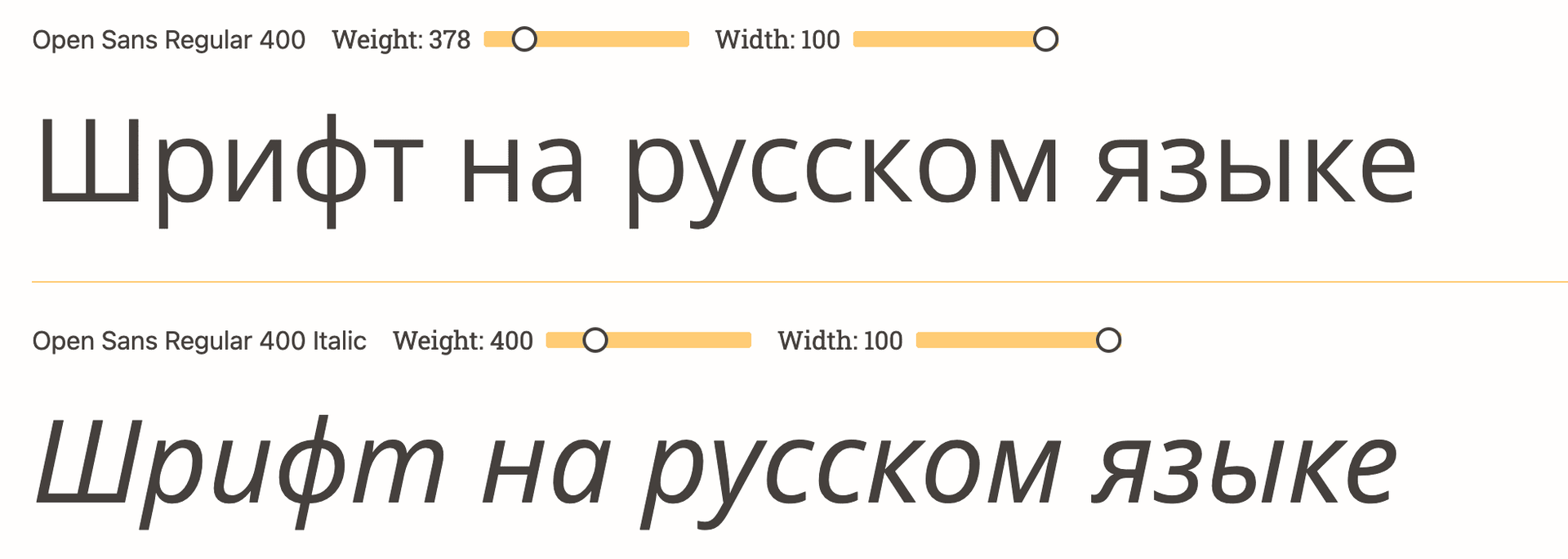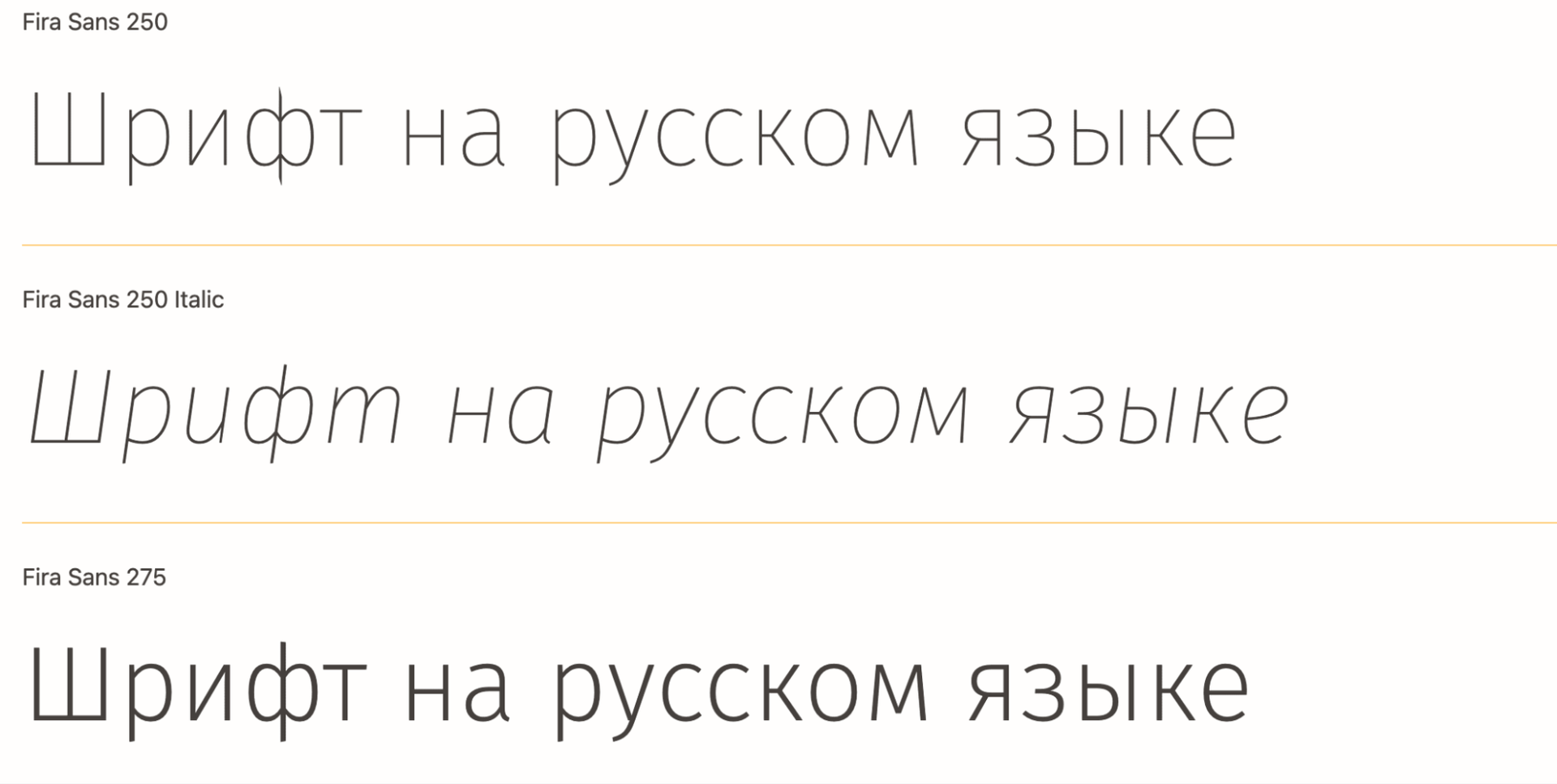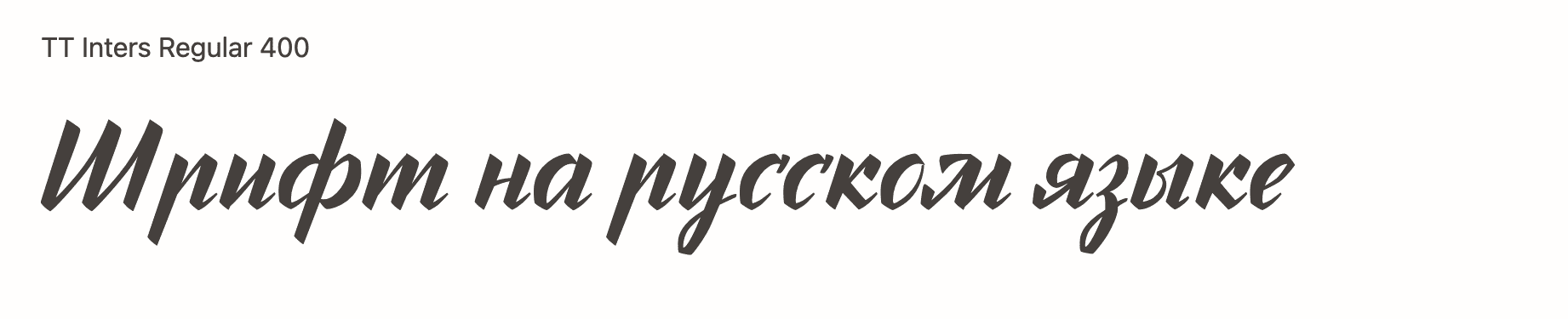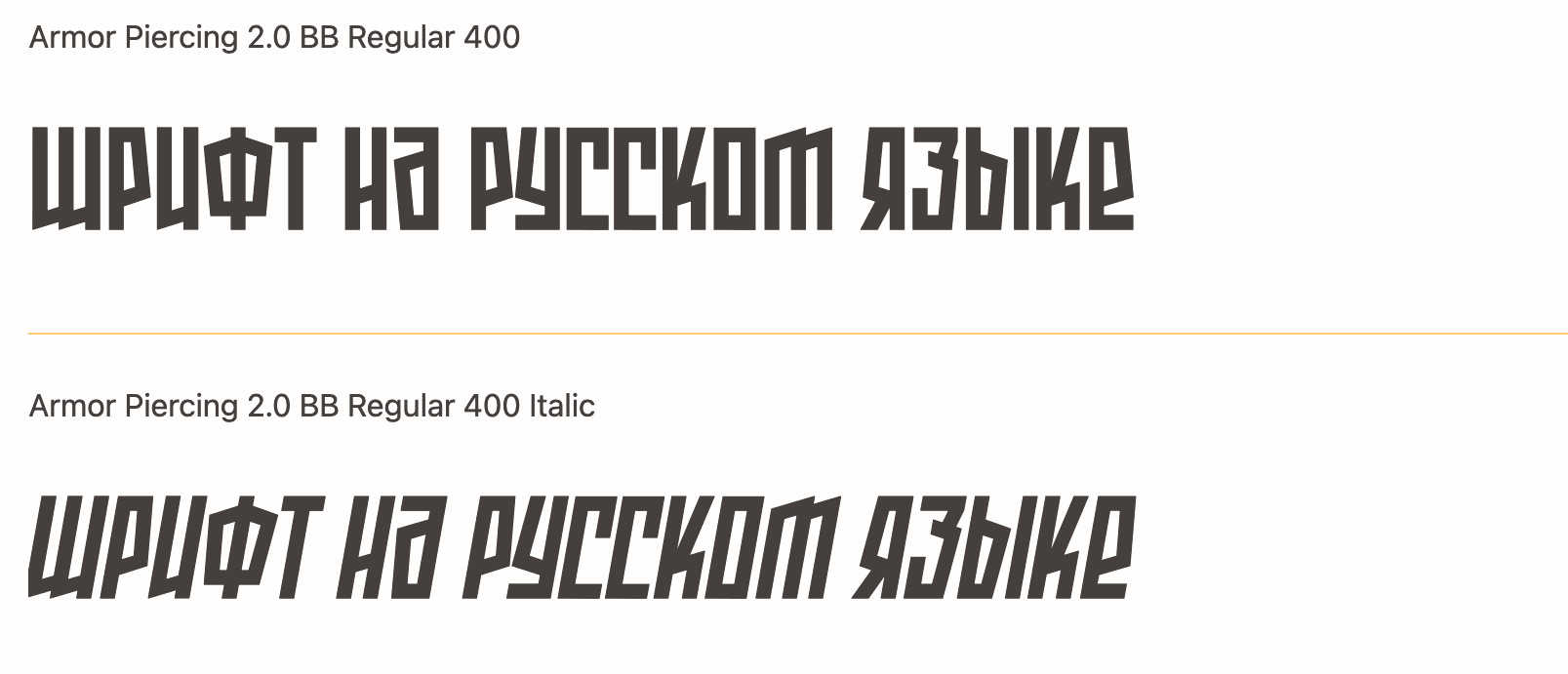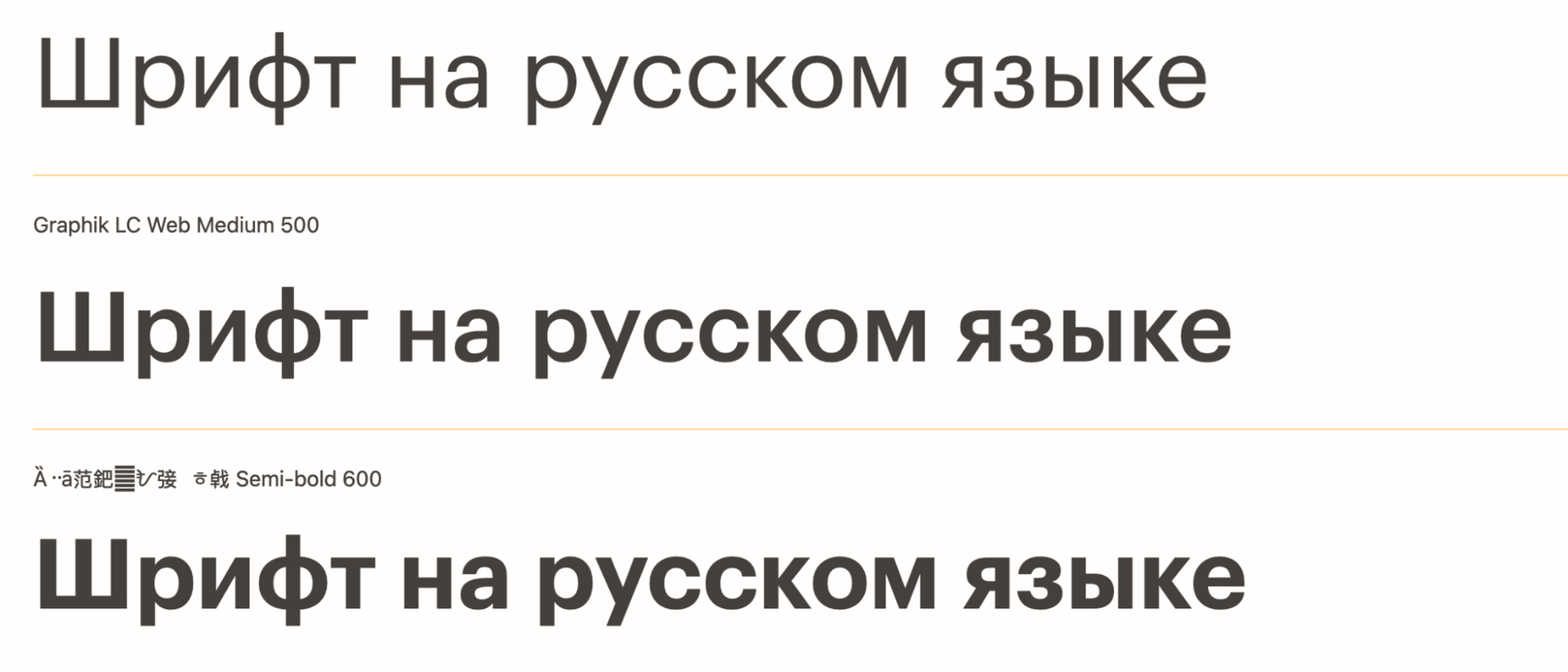
Красивые шрифты на русском:
как выбрать стильный кириллический шрифт для сайта, бренда и дизайна
В этой статье вы найдёте интересные шрифты на русском языке. Они отлично адаптированы под кириллицу и вы сможете использовать их для создания своего уникального стиля.
Красивый шрифт на русском – это не просто эстетика, а инструмент, который влияет на восприятие бренда, читаемость текста и общее впечатление от дизайна. Для заголовков, рекламы, соцсетей и айдентики особенно важно выбирать шрифты с качественной кириллицей, потому что у многих гарнитур русские буквы проработаны хуже латиницы.
Почему важно выбирать шрифт с хорошей кириллицей
Кириллица требует отдельного внимания: в ней есть буквы с вертикальными штрихами, сложные сочетания и знаки вроде «й» и «ё», которые должны выглядеть гармонично и читаться без усилий. Именно поэтому лучше брать шрифты, изначально созданные или доработанные под кириллицу, а не просто «подставленные» русские символы.
Для сайта это особенно важно, потому что типографика влияет на удобство чтения, доверие к проекту и визуальную цельность страницы. Для заголовков подходят более выразительные гарнитуры, а для основного текста нейтральные и хорошо читаемые шрифты без засечек.
Какие бывают красивые шрифты
Условно красивые шрифты на русском можно разделить на несколько групп. Это помогает быстро подобрать подходящий вариант под задачу, а не выбирать «на глаз».
• Гротески – современные шрифты без засечек, которые выглядят чисто и универсально. Они подходят для сайтов, интерфейсов, корпоративных страниц и технологичных брендов.
• Антиквы – шрифты с засечками, которые добавляют ощущение классики, статуса и элегантности. Их часто используют в журналах, премиальных проектах и брендовых материалах.
• Декоративные шрифты – акцентные варианты для заголовков, афиш, постеров, упаковки и социальных сетей. Они создают вау-эффект, но не подходят для длинных текстов.
• Рукописные и скриптовые – подходят для приглашений, логотипов, праздничных макетов и акцентных элементов, но требуют осторожности из-за читаемости.
Примеры красивых шрифтов на русском
Ниже мы указали проверенные примеры шрифтов, которые часто рекомендуют для кириллицы и которые можно использовать в разных типах проектов.
Graphik – это современный геометричный шрифт с очень аккуратной кириллицей. Он выглядит строго, чисто и профессионально, поэтому отлично подходит для брендов, которые хотят произвести впечатление надежности и современности. Такой шрифт часто используют в заголовках, на корпоративных сайтах, в презентациях и в digital-материалах, где важны стиль и четкость. Особенно хорошо он работает в проектах, где нужен минимализм без лишней декоративности.
TT Inters — современный геометрический гротеск с чистыми формами и аккуратной, «технологичной» эстетикой. Он выглядит строго и собранно, но при этом остаётся достаточно нейтральным, чтобы не перетягивать внимание на себя. Благодаря хорошей читаемости и сбалансированным пропорциям TT Inters часто используют в интерфейсах, бренд-дизайне, презентациях и деловой коммуникации.
Fira Sans – современный, открытый и дружелюбный шрифт, который хорошо смотрится, как в интерфейсах, так и в печатных материалах. У него читаемая форма букв и достаточно гибкий характер, поэтому он подходит для сайтов, документов, презентаций и корпоративных материалов. Fira Sans воспринимается чуть живее, чем совсем нейтральные шрифты, но при этом остается строгим и удобным для чтения. Это хороший выбор для проектов, где важны ясность и аккуратность.
Open Sans – универсальный шрифт, который давно стал классикой для веба. Его легко читать, он выглядит мягко и дружелюбно, а кириллица у него хорошо сбалансирована. Такой шрифт часто используют для блогов, коммерческих сайтов, лендингов, презентаций и любых текстовых блоков, где важно не утомлять пользователя. Open Sans подходит для проектов, которым нужен понятный и нейтральный визуальный тон.
Armor Piercing Cyrillic – это выразительный дисплейный шрифт с агрессивной, «индустриальной» подачей и ярко выраженным характером. Он построен на контрасте жёстких форм и плотной ритмики, из-за чего воспринимается как мощный, акцентный инструмент для заголовков и визуальных ударных элементов. Кириллическая часть сохраняет ту же экспрессию, что и латиница, поэтому шрифт выглядит цельно в многоязычных макетах.